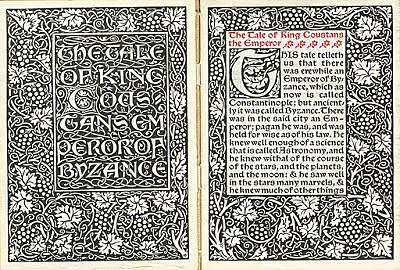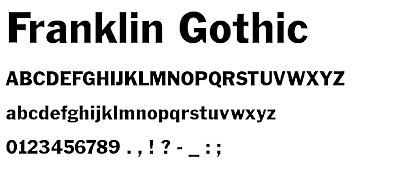
En Italia encontramos dos tipógrafos pertenecientes al siglo XV: N. Jenson, creador de la tipo Old Style.
La tipografía como tal surge con la imprenta de Gutemberg, puesto que la tipografía es una manera mecánica describir, y con esta imprenta es la primera vez que se crea escritura de manera mecánica ayudada de los tipos móviles. La imprenta nace en Maguncia en 1450
En Francia, en el siglo XVI, encontramos a C.Garamond, este hombre se dedicaba a hacer los tipos móviles y a venderlos, podríamos considerarle como el primer tipográfico.
En Inglaterra en el siglo XVIII nos topamos con W.Caslon y con J.Baskerville. Con la tipografía Caslon (1724) la técnica mejora mucho, esta tipografía fue exportada a EEUU, esto produjo que los primeros documentos Estadounidenses de gran relevancia, como la declaración de independencia, fuesen escritos con ella. Esta tipografía aporta contraste entre linea finas y gruesas, por lo que comenzaron a perderse pequeños detalles.
Surgen avances como la negrita, palo seco o las titulares.
La negrita son fuentes con contornos muy marcados.
El palo seco surgió con la tipografía Caslon.
Los tipos titulares aparecen con la tipografía de estilo victoriano.
Estos avances en la industria tipográfica comenzó a molestar a muchos que comenzaron a reivindicar el estilo clásico que se había estado teniendo antes de que surgieran tantos cambios. -
W.Morris pertenece al grupo Arts and Crafts, este grupo era el que reivindica una vuelta a lo tradicional, para ello creó su imprenta Kelmscott.
Surgió la Linotipia y la monotipia. La primera aparece gracias a Otto Mer Genthaler en 1886, se asemeja a la máquina de escribir, utiliza lingotes que funden las lineas de texto completa, se utilizaba en la prensa. La Monotipia apareció con Tolbert Lansto en 1887, se utilizaba en la industria de los libros, en este caso va letra por letra en vez de por lingotes.
En el 1900 nos topamos con las nuevas vanguardias que conviven con el Art Nouveau (Modernismo en España) muy influenciado por la pintura, y es considerado precursor del diseño gráfico. Se utiliza una tipografía muy de pintura que parece dibujada. Define la belleza del estilo y la línea tradicional.
En este periodo encontramos tipografías características como la Gismonda, Isadora, Perry Gothic y sobretodo la Arnold Böcklin. -
Franklin Gothic (1902) de Morris Fuller Benton.